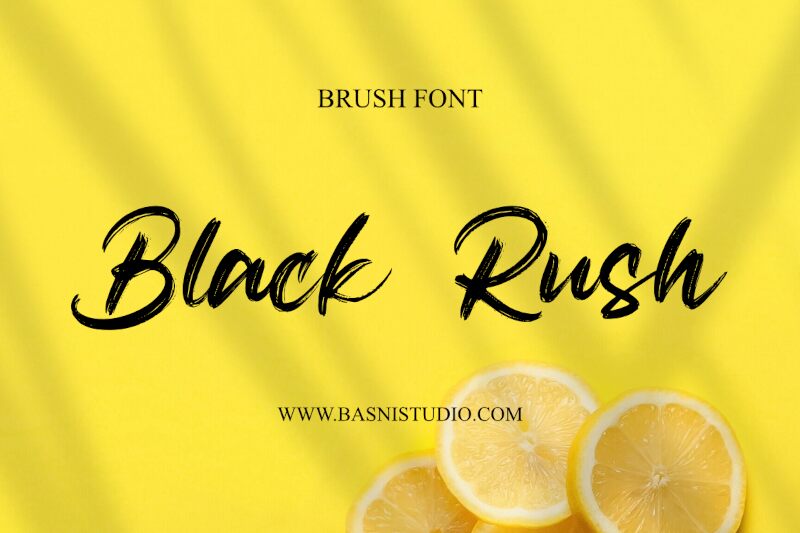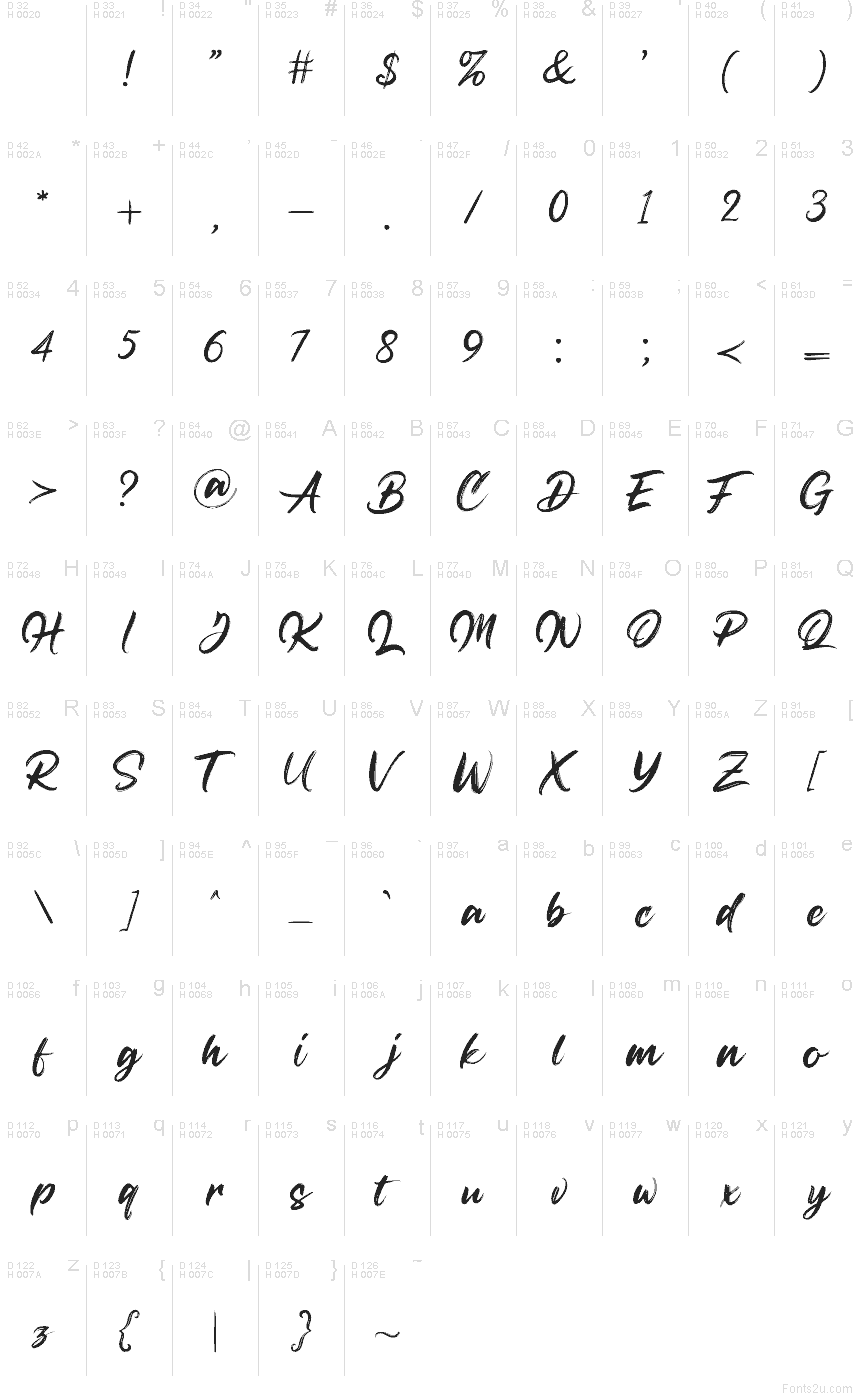
Blackrush от Basni.std — это бесплатный шрифт в стиле грубого рукописного письма (rough-brush script), создающий ощущение быстрой, живой росписи. Буквы перетекают одна в другую длинными связными мазками, а сухие края и «царапаная» текстура придают им небрежный, естественный вид — словно надпись сделана одним движением кисти с краской.
Шрифт отлично подойдет для брендинга, постеров, оформления музыкальных релизов, упаковки и заголовков в соцсетях, где нужен бесплатный шрифт, передающий движение и «человеческий» почерк. Используйте его для коротких заголовков, обложек или логотипов, когда хотите, чтобы длинные росчерки и фактурные соединения стали главной фишкой вашего дизайна.